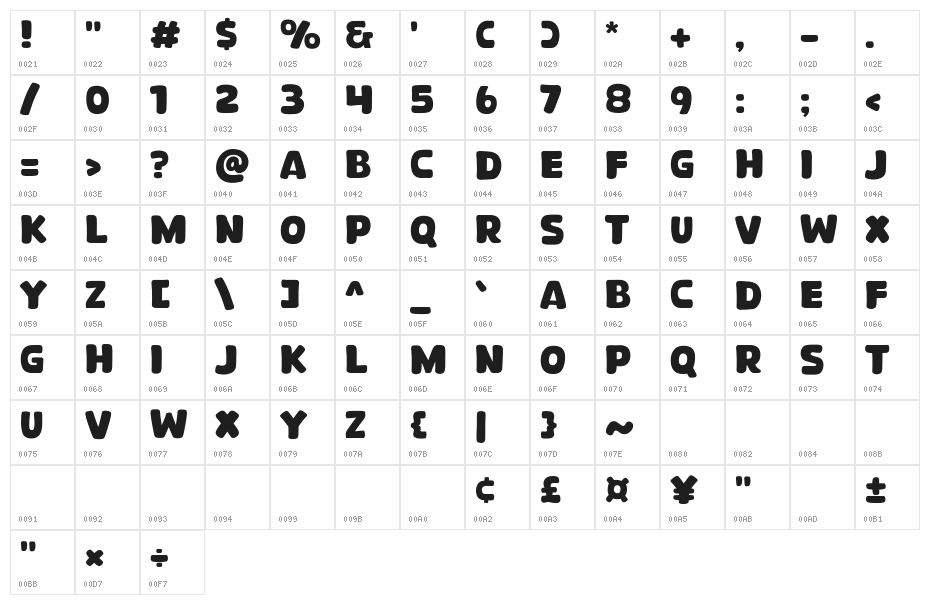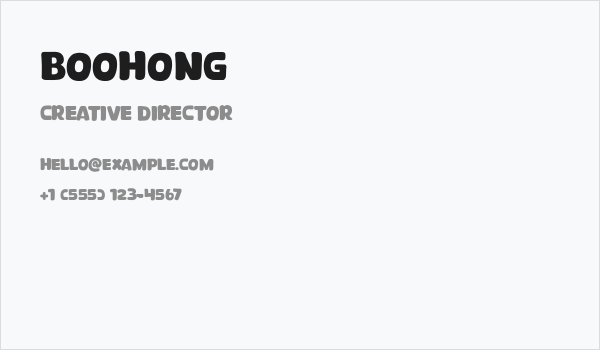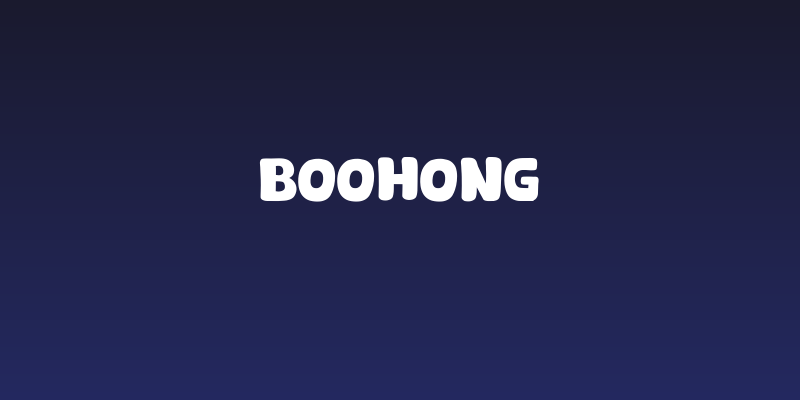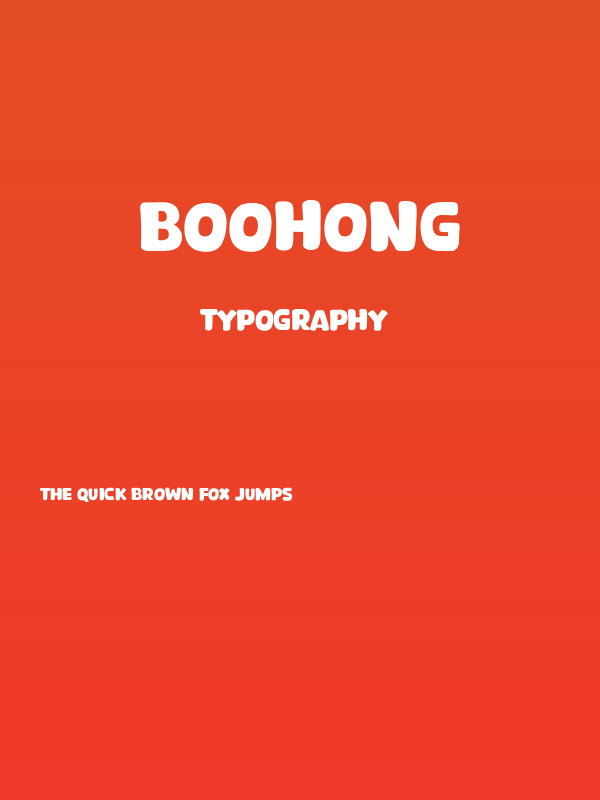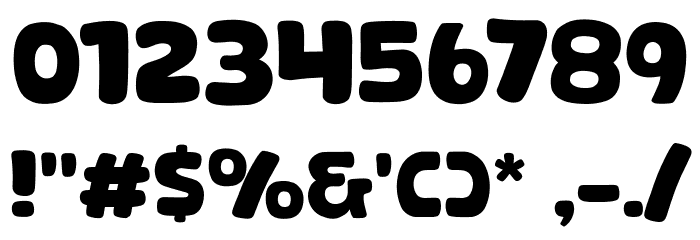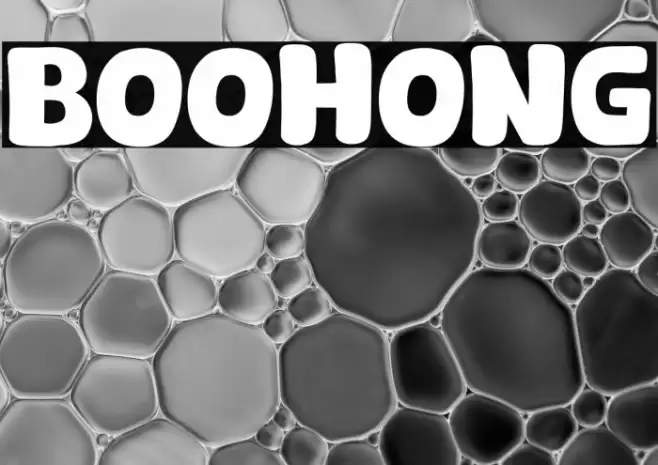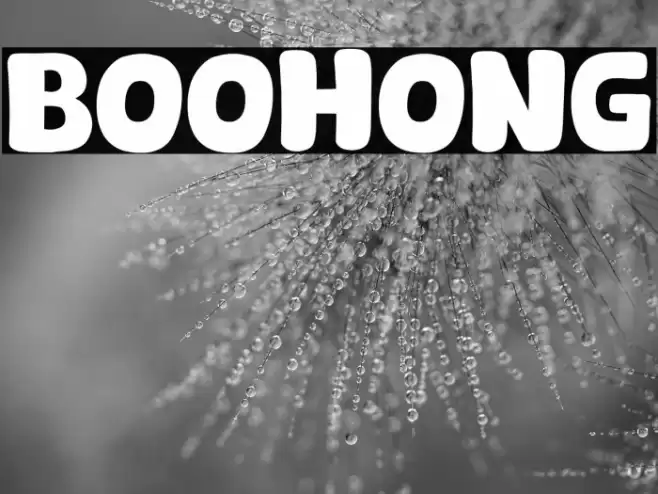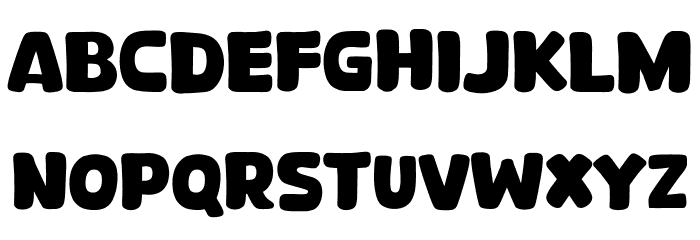
Boohong Font
| Gesamtstil | Playful |
| Vorgeschlagene Projekte | Ideal for children's books, playful branding, casual invitations, and eye-catching headlines. |